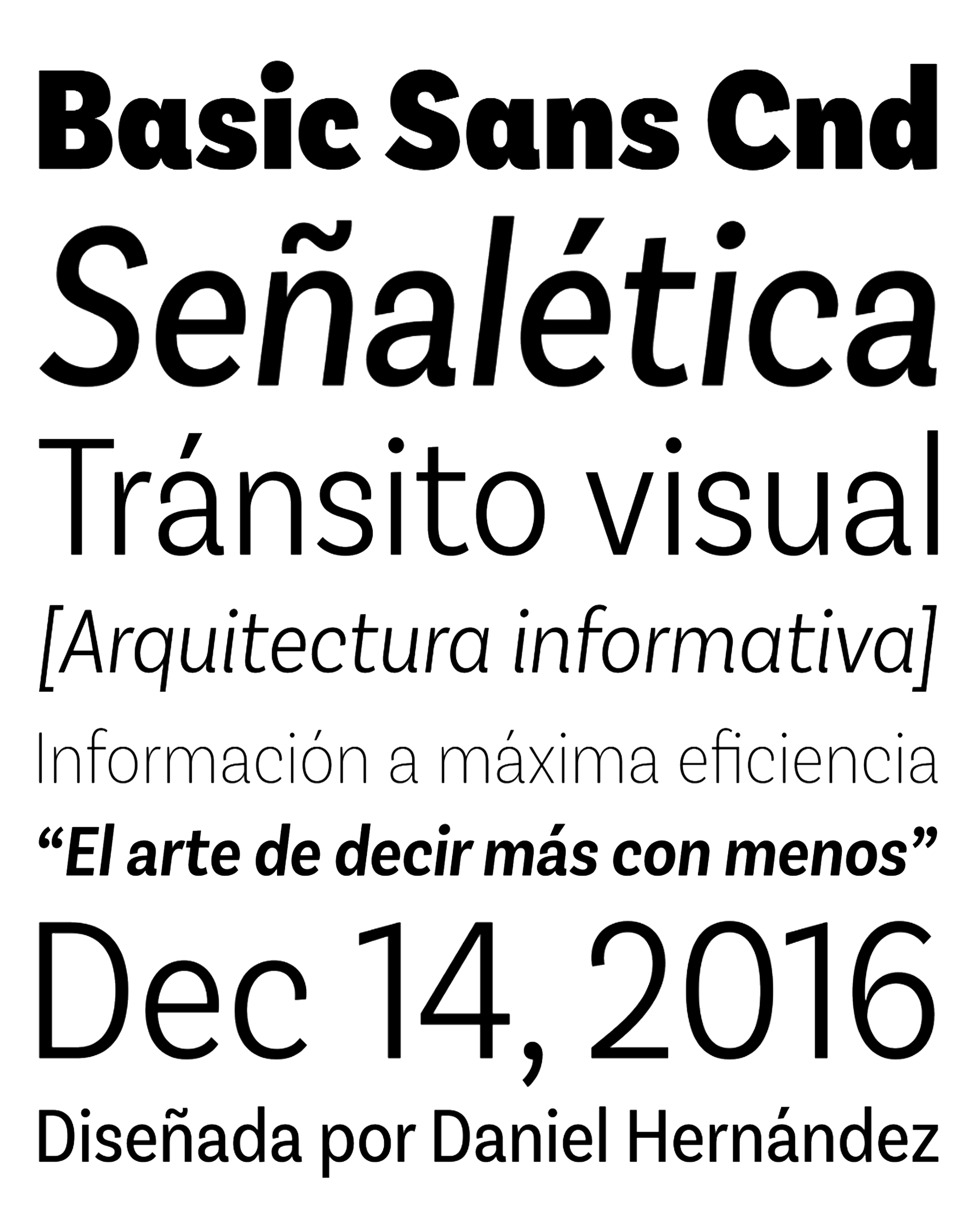
| Año | 2016 |
| Créditos | Daniel Hernández |
| Descripción | Basic Sans Cnd: Una nueva sans. Diseñada por Daniel Hernández Basic Sans Cnd es una versión más estrecha de Basic Sans. Es una familia de rasgos grotescos con un estilo funcional, neutro y aparentemente limpio que busca mantener una apariencia neutra (o básica) sobre el papel, pero incluyendo muchos detalles que le dan una personalidad única. Basic Sans Cnd es un tipo de letra sin gracias muy adecuado para proyectos editoriales, textos de tamaño medio, marcas, carteles, titulares y mucho más. Esta familia tipográfica está disponible en 7 pesos, desde Thin hasta Black, además de cursivas a juego, y cuenta con un conjunto de 416 caracteres compatibles con 206 idiomas diferentes. |
| Familia(s) | Thin, Thin It, Extra Light It, Light, Light It, Regular, Regular It, Semi Bold, Semi Bold It, Bold, Bold It, Black, Black It, Alt Thin, Alt Thin It, Alt Extra Light It, Alt Light It, Alt Regular, Alt Regular It, Alt Semi Bold, Alt Semi Bold It, Alt Bold, Alt Bold It, Alt Black, Alt Black It |